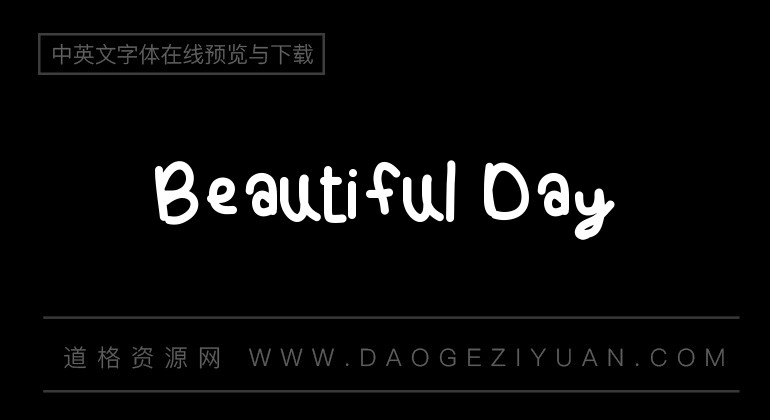
Beautiful Day
Beautiful Day 是一种手写风格的字体,它的特点是线条自然流畅、圆润柔和,给人一种温馨、舒适的感觉。这种字体适合用来设计贺卡、海报、广告等需要营造温馨氛围的场合,也可以用在商标、品牌标识等设计中。Beautiful Day 字体具有多种字重和风格,方便设计师根据需要选择不同的样式。
Beautiful Day是一款非常不错的手写艺术字体,具有很好的视觉感,适合于文化类的宣传设计、商业类品牌的广告和产品包装设计以及个性化文字排版等较多场景。